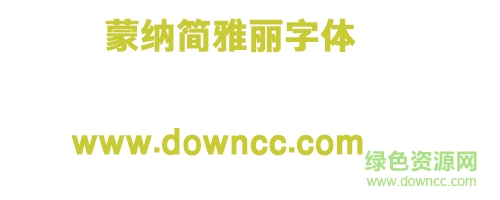
蒙納簡雅麗字體是一款非常優(yōu)美的字體,主要表現(xiàn)為豎筆畫較粗,給人以成熟穩(wěn)重之感,適合作為標題使用。小編為大家提供免費下載地址。快來綠色資源網(wǎng)吧
這是一款由蒙納公司推出的簡體字體,在宋體字體的基礎(chǔ)上修改而成,看起來別有一番特色,美觀大方,經(jīng)常被應(yīng)用于書籍印刷、海報宣傳、廣告設(shè)計等等方面。